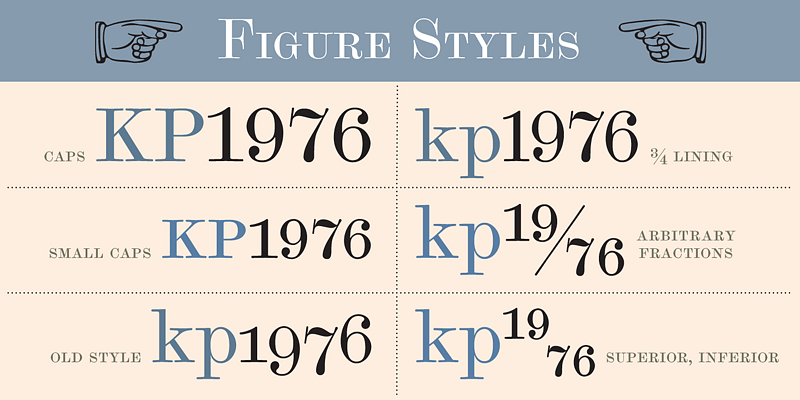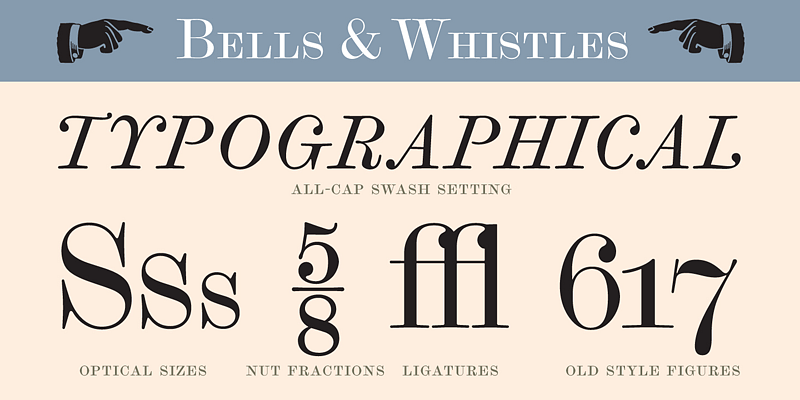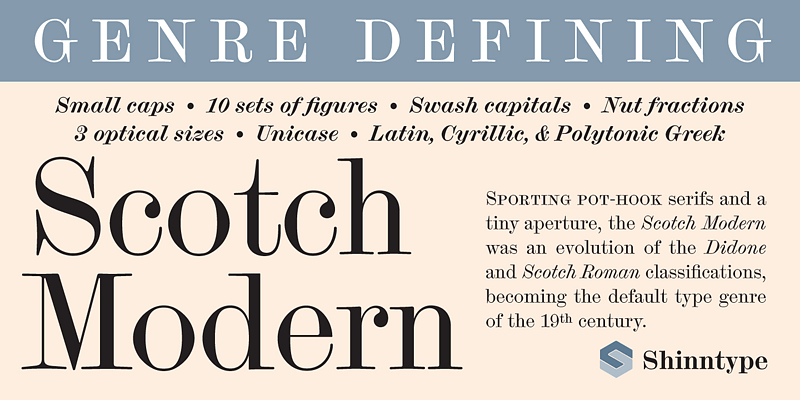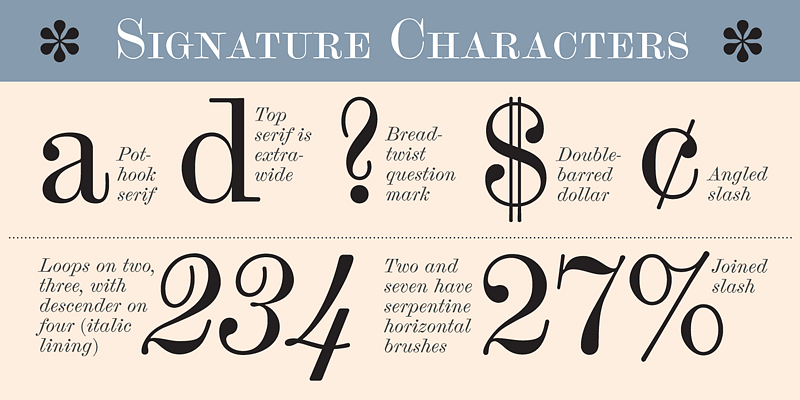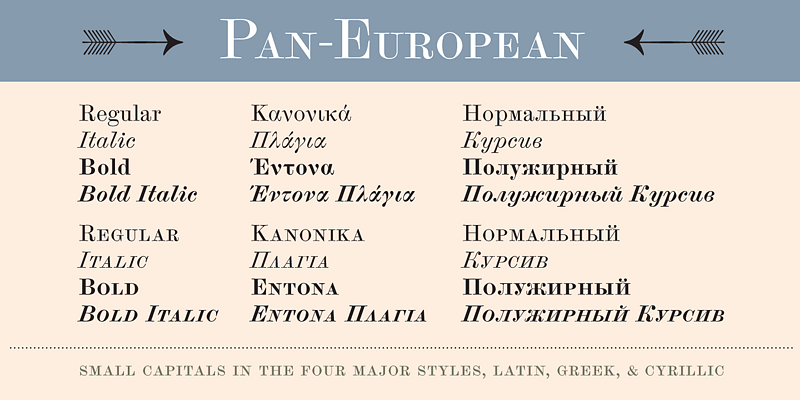
Durch die Rekontextualisierung der 10-Punkt-Schrift eines wissenschaftlichen Berichts aus dem Jahr 1873 hat Shinn elegante, raffinierte, mikro-detaillierte Vektorzeichnungen nach Augenmaß erstellt, ohne sich wie üblich auf Scans und Durchpausen zu verlassen – das Ergebnis ist einzigartig authentisch. Mit optischen Größen, zahlreichen OpenType-Funktionen und einer umfangreichen Sprachabdeckung ist diese Scotch ganz großartig.
Diese Designs von Nick Shinn sind fest in der europäischen und nordamerikanischen typografischen Tradition verwurzelt, die sich ständig weiterentwickelt. Eine zuverlässige Textschrift mit allen Details professioneller Typografie und eine intelligente Display-Schrift mit Liebe zum makellosen Detail.